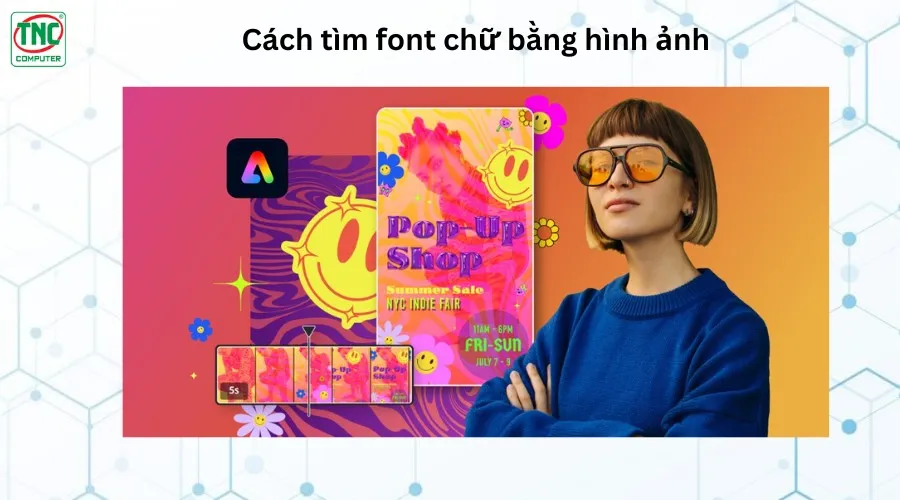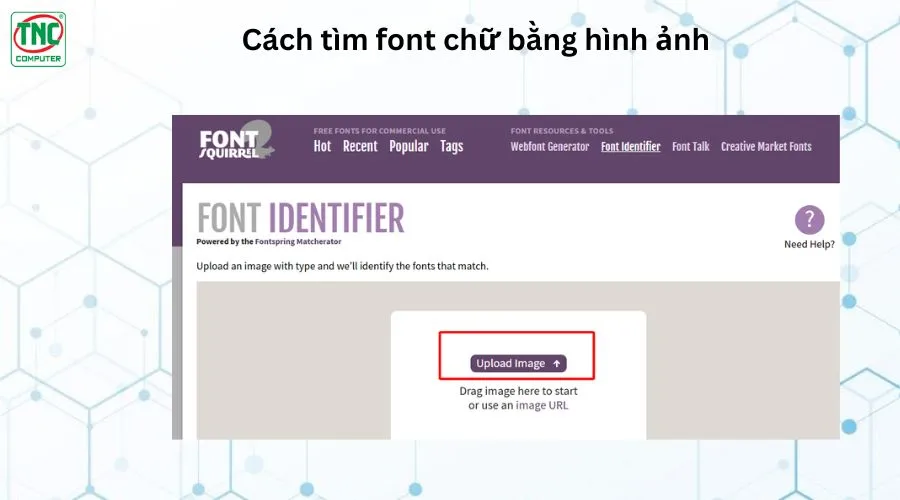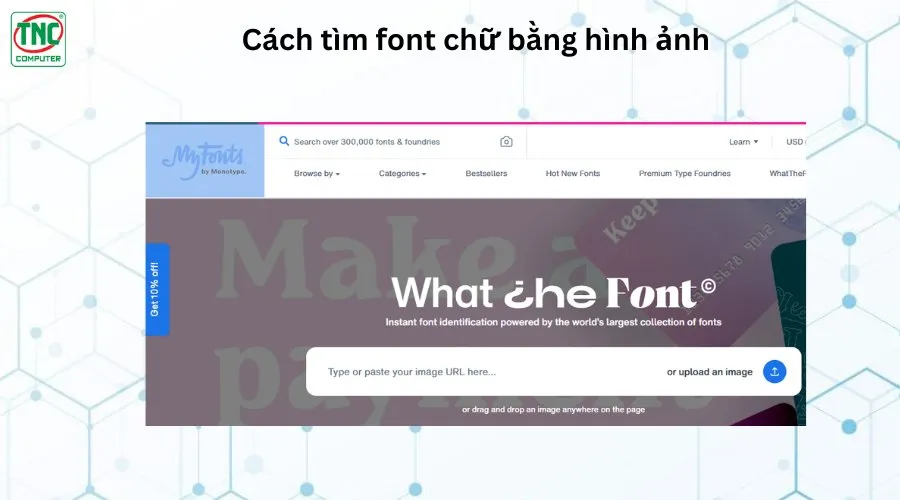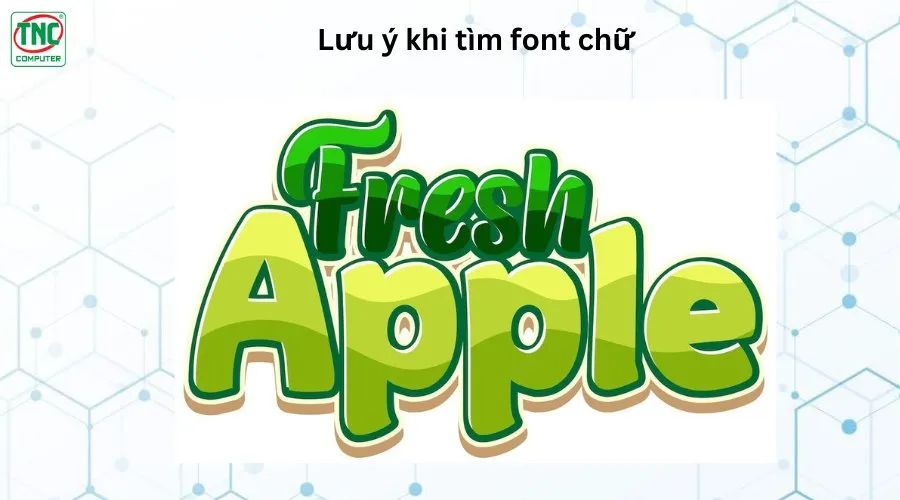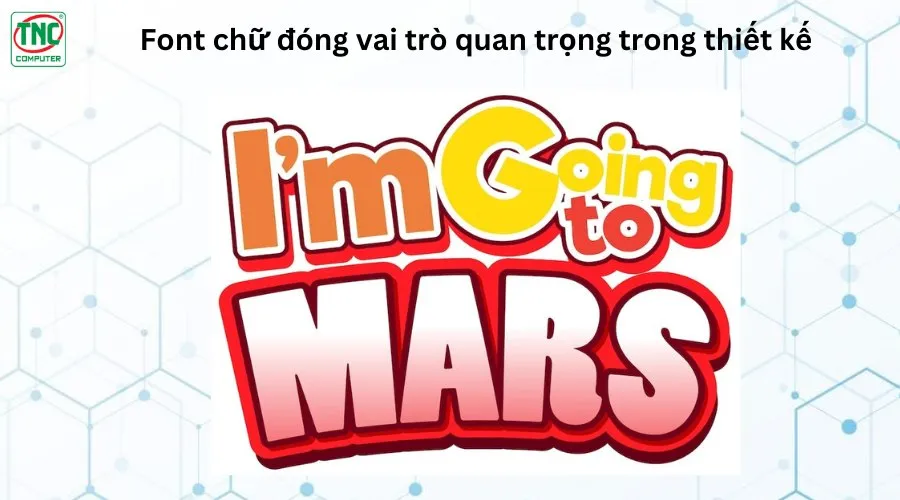
Hướng dẫn cách tìm font chữ bằng hình ảnh siêu tốc
Trong quá trình thiết kế, đôi khi bạn bắt gặp một font chữ đẹp nhưng không biết tên để sử dụng. Thay vì mất hàng giờ tìm kiếm thủ công, bạn có thể dùng công cụ nhận diện font chữ qua hình ảnh. Những công cụ này giúp xác định font dựa trên đặc điểm chữ cái, giúp bạn tìm được font tương tự hoặc chính xác trong vài giây. Vậy làm thế nào để tìm font chữ bằng hình ảnh một cách nhanh chóng và hiệu quả? Hãy cùng khám phá!
Font chữ đóng vai trò quan trọng trong thiết kế
Font chữ đóng vai trò quan trọng trong thiết kế, vì nó không chỉ truyền tải nội dung mà còn ảnh hưởng đến cảm xúc và trải nghiệm của người xem. Một font chữ phù hợp có thể làm nổi bật thông điệp, tăng tính thẩm mỹ và tạo dấu ấn riêng cho thương hiệu. Ngược lại, việc chọn sai font có thể làm giảm tính chuyên nghiệp và gây khó khăn trong việc tiếp nhận thông tin.
Truyền tải thông điệp và cảm xúc
Mỗi font chữ mang một cá tính và cảm xúc riêng. Ví dụ, font serif thường tạo cảm giác trang trọng, cổ điển, trong khi font sans-serif mang lại sự hiện đại, tối giản.
Việc lựa chọn font chữ phù hợp giúp truyền tải chính xác thông điệp mà nhà thiết kế muốn gửi gắm, đồng thời khơi gợi cảm xúc phù hợp ở người xem.
Tạo dựng nhận diện thương hiệu
Font chữ là một phần quan trọng trong bộ nhận diện thương hiệu. Một font chữ độc đáo và nhất quán giúp thương hiệu trở nên dễ nhận biết và ghi nhớ.
Việc sử dụng font chữ phù hợp giúp xây dựng hình ảnh thương hiệu chuyên nghiệp và đáng tin cậy.
Tăng cường khả năng đọc và hiểu
Một font chữ dễ đọc giúp người xem tiếp nhận thông tin một cách dễ dàng và thoải mái.
Việc lựa chọn kích thước, khoảng cách và kiểu chữ phù hợp giúp tối ưu hóa khả năng đọc, đặc biệt là đối với các văn bản dài.
Tạo điểm nhấn và sự chú ý
Font chữ có thể được sử dụng để tạo điểm nhấn cho các tiêu đề, khẩu hiệu hoặc thông tin quan trọng.
Việc kết hợp các font chữ khác nhau một cách hợp lý giúp tạo ra sự tương phản và thu hút sự chú ý của người xem.
Thể hiện phong cách thiết kế
Font chữ góp phần thể hiện phong cách thiết kế tổng thể của tác phẩm. Ví dụ, một thiết kế mang phong cách vintage có thể sử dụng font chữ cổ điển, trong khi một thiết kế hiện đại có thể sử dụng font sans-serif tối giản.
Cách tìm font chữ bằng hình ảnh
Nếu bạn bắt gặp một font chữ đẹp trên mạng hoặc trong một thiết kế nào đó nhưng không biết tên, bạn có thể sử dụng các công cụ nhận diện font chữ bằng hình ảnh. Dưới đây là các bước đơn giản để tìm font chữ qua ảnh:
Sử dụng công cụ trực tuyến
Có nhiều trang web hỗ trợ tìm kiếm font chữ bằng hình ảnh, chẳng hạn như:
• WhatTheFont (MyFonts) – Công cụ phổ biến và dễ sử dụng.
• Font Squirrel Matcherator – Nhận diện font miễn phí, hỗ trợ nhiều định dạng.
• Adobe Fonts (Typekit) – Tích hợp với Adobe, phù hợp cho nhà thiết kế.
WhatTheFont (MyFonts)
WhatTheFont là công cụ nhận diện font chữ của MyFonts, giúp bạn tìm kiếm tìm font qua hình ảnh.
Cách sử dụng
• Truy cập trang web WhatTheFont.
• Tải lên hình ảnh có chữ mà bạn muốn tìm font.
• Công cụ sẽ quét và đề xuất các font tương tự.
Ưu điểm
• Hỗ trợ nhận diện nhiều kiểu chữ khác nhau.
• Dễ sử dụng, không cần tài khoản.
• Gợi ý nhiều font từ thư viện MyFonts.
Nhược điểm
Font Squirrel Matcherator
Đây là một công cụ miễn phí giúp nhận diện font từ hình ảnh, tương tự như WhatTheFont nhưng có nhiều font miễn phí hơn.
Cách sử dụng
• Truy cập Font Squirrel Matcherator.
• Tải lên hình ảnh chứa văn bản.
• Công cụ sẽ phân tích và đề xuất các font tương tự.
Ưu điểm
• Cung cấp nhiều font miễn phí.
• Hỗ trợ tìm kiếm font tốt cho thiết kế.
• Không yêu cầu đăng ký tài khoản.
Nhược điểm
Độ chính xác có thể không cao bằng WhatTheFont.
Adobe Fonts (Typekit)
Adobe Fonts (trước đây là Typekit) là một thư viện font chữ chuyên nghiệp của Adobe, cho phép người dùng tìm và đồng bộ font để sử dụng trong các phần mềm như Photoshop, Illustrator, InDesign.
Cách sử dụng:
• Truy cập Adobe Fonts.
• Tìm kiếm font theo tên, phong cách hoặc tải lên hình ảnh để nhận diện.
• Đồng bộ font với tài khoản Adobe Creative Cloud để sử dụng.
Ưu điểm
• Thư viện font đa dạng, chất lượng cao.
• Dễ dàng đồng bộ với phần mềm Adobe.
• Có nhiều font miễn phí cho người dùng Adobe.
Nhược điểm
Lưu ý khi tìm font chữ
Để tìm được font chữ chính xác hoặc gần giống nhất, bạn cần chú ý một số điều sau:
Chất lượng hình ảnh
Sử dụng hình ảnh có độ phân giải cao để công cụ nhận diện tốt hơn.